使用photoshop打造爆炸文字效果
本教程将向您展示如何使用几张色彩鲜艳的纹理图像,使用Photoshop动作和一些烟雾和纹理叠加,以创建简单,多彩的爆炸文字效果。让我们开始吧
先看下效果
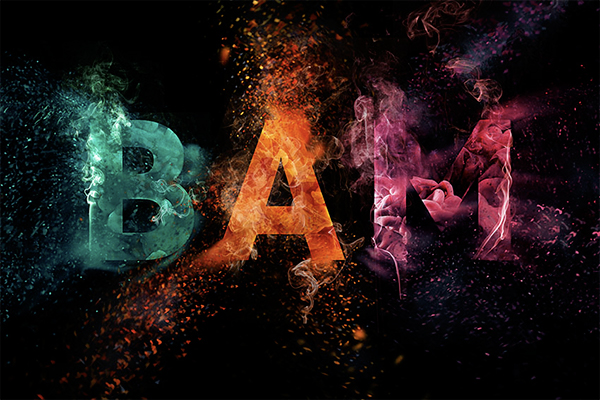
准备素材:网上可以下载很多这种彩色墨子的效果,或者彩色花朵。
1、如何制作背景和基本文字
步骤1、创建一个新的1500 x 1000 px文档,单击“图层”面板底部的“创建新的填充或调整图层”图标,选择“纯色”,然后将填充颜色设置为“黑色”。
第2步、输入bdm三个字母,将“大小”设置为500 pt,将“缩放”设置为50。如果您的文字不合适,您可以增加画布大小。这里字母b有点不是很美观,我们简单的调整他的形状。
2、如何使用图像纹理填充文本
步骤1、打开蓝色水墨纹理,放置文字层上面,右键-创建粘贴蒙板。图案便贴近了文字里。
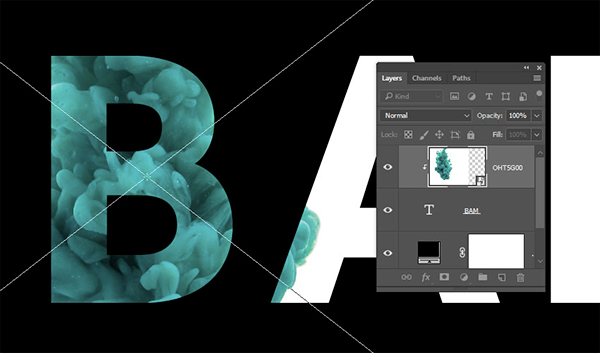
步骤2、选中字母b,使其变为选区,反向删除多余的图案。
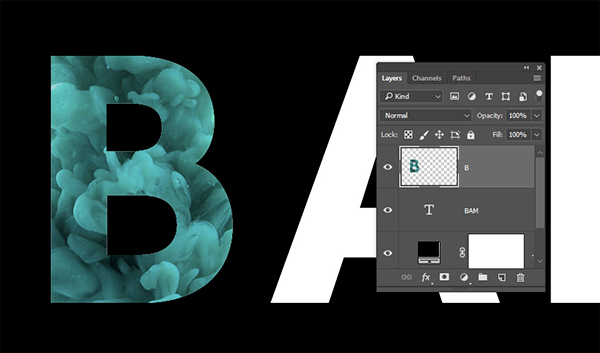
步骤5、重复相同的步骤将其他图像纹理添加到剩余的字母。 完成后,隐藏文本图层。
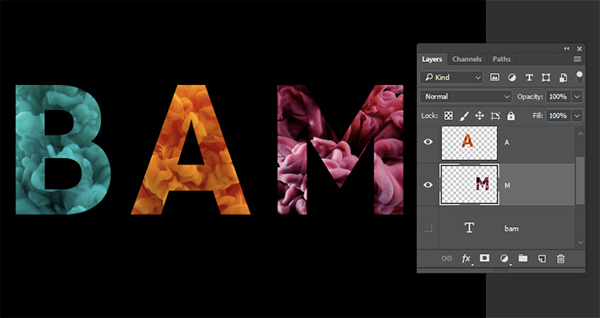
3、如何保存和加载选择
步骤1、选择除文本图层之外的所有图层,然后转到图层>合并图层。
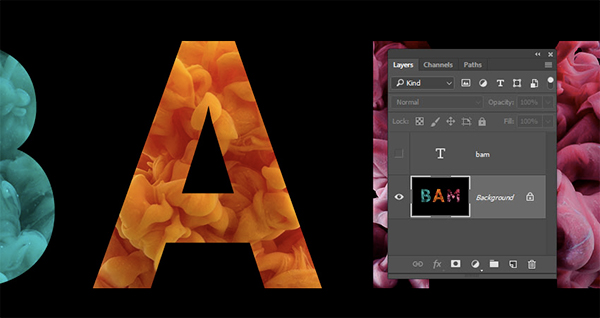
步骤2、点击文字图案,使他们变为选区。
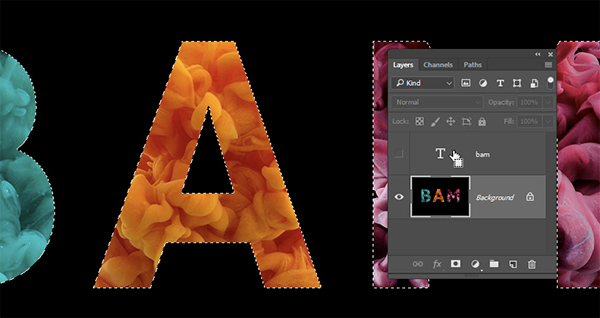
步骤3、转到选择>存储选区,然后在名称字段中键入文本。
步骤4、删除文本图层
我们将使用选择在文本区域中绘制,因此如果在任何时候您需要再次选择,您可以直接进入选择>载入选区,然后从“通道”菜单中选择“文本选择”。
4、如何使用沙尘暴Photoshop动作
步骤1、选择画笔工具,在所有图层之上创建一个新图层,并将其命名为画笔。 这个名字很重要,所以确保拼写正确。
步骤2、这是一个可选的步骤,但它有助于创建更具动态的结果。 打开“画笔”面板,并使用“刷子提示形状和形状动态”选项卡的这些设置。
步骤3、将前景颜色设置为您喜欢的任何颜色,然后开始绘制要分割的区域。动作带有多个方向选项(左,右,上,下和中)。 所以请记住你想要的部件被粉碎的方向。另外,请注意,零件将从涂漆区域内产生,这意味着刷子尺寸也会影响结果。
5、如何运行一个动作
步骤1、完成绘画后,按Command-D取消选择。打开“动作”面板,如果还没有,请加载动作,然后选择所需的方向。单击“动作”面板底部的“播放”选项图标以运行该动作,并等待其运行。 这可能需要几分钟的时间。
步骤2、获得结果后,您可以看到您仍然拥有“背景”和“刷”图层。 如果不喜欢结果,可以删除动作图层,对画笔层进行一些更改,然后再次运行该操作。
在这个过程中没有对错,这是试验和错误,直到你得到你喜欢的结果。
步骤3、一旦得到所需的结果,您可以查看所有的操作文件夹和图层,并对其中的任何一个进行调整。例如,在这里我将“粒子组”组缩小。 您可以继续进行任何其他更改,使用掩码删除不需要的区域,并尝试COLOR组中可用的不同选项。
6、如何添加烟雾和纹理叠加层
步骤1、将其中一个烟雾图像放置在其中一个字母的顶部,根据需要进行转换,并将其层的混合模式更改为滤色。
步骤2、转到图像>调整>色相/饱和度,选中“彩色”框,然后将“饱和度”更改为50。然后,拖动色调滑块,直到得到类似于字母纹理颜色的颜色,然后单击确定。
步骤3、在烟层添加一个蒙板,并删掉你不喜欢的任何区域。
步骤4、将其他烟雾图像添加到您拥有的其他字母,具有基于字母纹理颜色的不同颜色。将所有烟雾纹理层放在一组中,并将其命名为Smoke。
步骤5、将景观图像放置在所有图层的顶部,调整其大小以填充文档,并将其图层的混合模式更改为柔光,并将其不透明度更改为50%